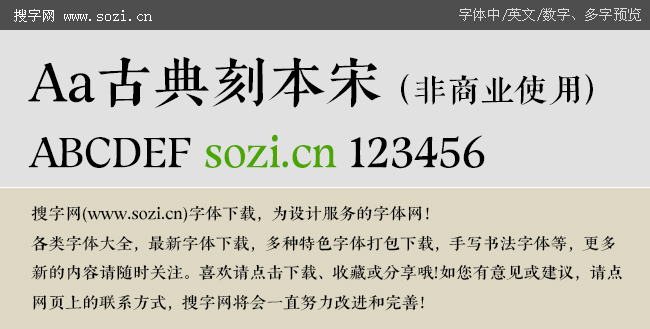
Aa古典刻本宋
搜字網(wǎng)給大家提供一款A(yù)a古典刻本宋(非商業(yè)使用)中文字體下載,Aa古典刻本宋是一款獨(dú)具特色的字體,汲取了康熙字典內(nèi)文宋體的精髓,并經(jīng)過(guò)現(xiàn)代化數(shù)字處理,煥發(fā)出簡(jiǎn)潔銳利的新生命。適合應(yīng)用于海報(bào)設(shè)計(jì)、包裝設(shè)計(jì)、網(wǎng)頁(yè)設(shè)計(jì)等應(yīng)用(此字體為個(gè)人非商用版,商用可以聯(lián)系QQ:1006760504)。